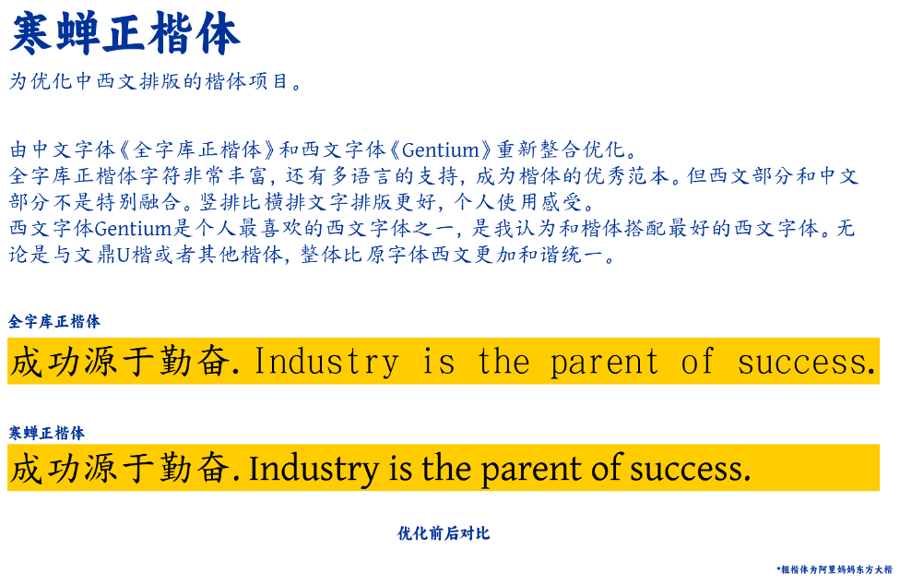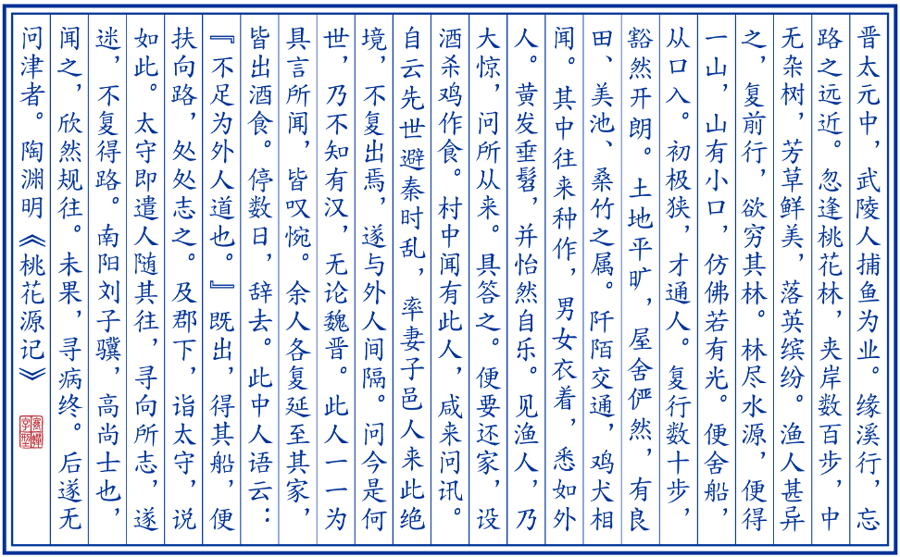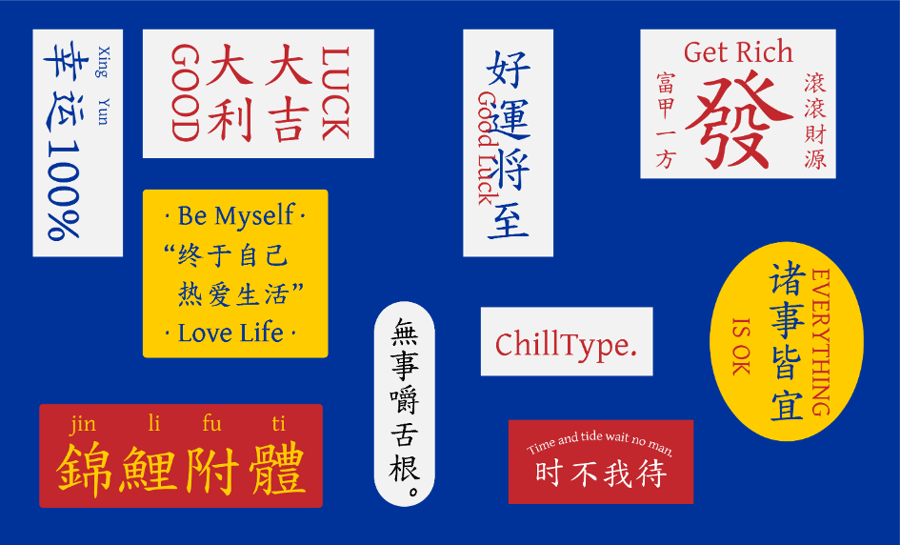
寒蝉正楷体(ChillKai)是由寒蝉字型开发的一款免费开源可商用的楷体字体。由中文字体《全字库正楷体》和西文字体《Gentium》整合而成,目的就是为优化中西文排版,使两者在排版上更加和谐统一。
寒蝉正楷体继承了全字库正楷体的字符多样性,不仅涵盖 GB/T 2312、现代汉语常用字表、现代汉语通用字表等简体中文编码中的全部字符,也包含了 Big5 编码中的常用汉字,还支持日文假名等,可以满足多种语言文字的排版需求。
设计上,寒蝉正楷体严格遵循楷书的字形结构。重心平稳,笔画规范,兼具传统楷书的端庄大气,也确保了极佳的阅读性和辨识度。不过个人感觉,寒蝉正楷体的竖排比横排排版效果要更好一些。